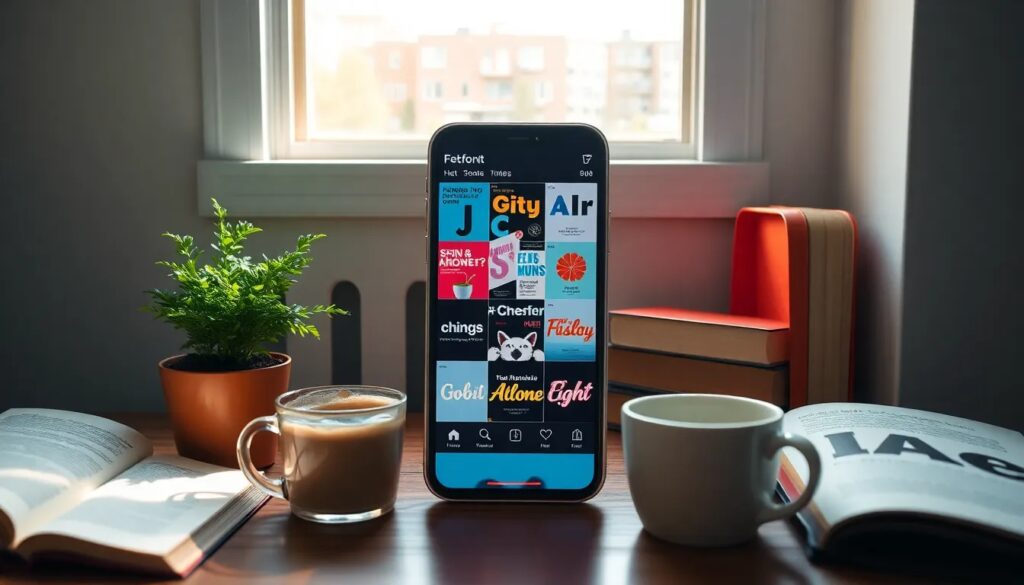
Cool fonts instagram para destacar tu perfil
Generador de fuentes para Instagram: cool fonts instagram
Las cool fonts instagram se han vuelto una herramienta imprescindible para quienes desean personalizar su perfil y hacerlo más atractivo. Con un generador de fuentes, puedes experimentar con diferentes estilos de texto que capturan la atención de tus seguidores.
Utilizando caracteres Unicode, estos generadores ofrecen una amplia variedad de fuentes que puedes usar en tu biografía, publicaciones y más. Esto te permite no solo diferenciarte, sino también mostrar un estilo único que refleje tu personalidad.
¿Para qué sirven las fuentes para Instagram?
Las fuentes para Instagram sirven principalmente para destacar tu perfil y hacer que tu contenido sea más atractivo. Al personalizar tu texto, puedes atraer más seguidores y mantener el interés de tus visitantes. Las fuentes estilizadas añaden un toque de originalidad que puede ser muy efectivo.
Además, usar fuentes diferentes puede ayudar a que tu biografía sea más memorable y fácil de leer. La claridad y el estilo son aspectos que la audiencia valora, y las fuentes adecuadas pueden jugar un papel crucial en esto.
• Ayudan a diferenciarte de otros perfiles.
• Permiten expresar tu personalidad de forma visual.
• Facilitan la creación de contenido que resuena con tu audiencia.
¿Cómo generar cool fonts instagram para mi perfil?
Generar cool fonts instagram es un proceso sencillo que puedes realizar en minutos. Existen múltiples generadores gratuitos en línea que te permiten introducir tu texto y recibir distintas opciones de fuentes estilizadas.
Recuerda que algunos estilos pueden no ser visibles en todos los dispositivos. Es recomendable probar cómo se ven en diferentes plataformas antes de hacer cambios permanentes en tu perfil.
¿Cuáles son las mejores fuentes estilizadas para Instagram?
En el ámbito de las fuentes modernas para Instagram que llamen la atención, hay varias opciones populares que destacan. Algunas de las más utilizadas incluyen:
• Fuentes cursivas, que aportan un toque elegante.
• Fuentes góticas, ideales para un estilo más atrevido.
• Fuentes decorativas, perfectas para hacer tu biografía única.
• Fuentes de tipo máquina de escribir, que evocan un estilo retro.
Además, puedes encontrar fuentes que imitan el estilo de la escritura a mano, lo que puede hacer que tu perfil se sienta más personal. La elección de la fuente debe alinearse con la estética general que deseas proyectar.
¿Qué tipos de fuentes se pueden crear con un generador?
Un generador de fuentes gratis para Instagram que puedes usar ahora te permite crear diversos estilos que se adaptan a tus necesidades. Algunos de los tipos de fuentes que puedes generar incluyen:
• Fuentes normales: ideales para un uso cotidiano
• Fuentes en negrita: para destacar información importante
• Fuentes con símbolos decorativos: que añaden un elemento visual único
Las combinaciones son prácticamente infinitas, lo que te permite ser creativo y experimentar hasta encontrar el estilo que más te guste. Recuerda que las fuentes pueden influir en la percepción de tu perfil, así que elige sabiamente.
¿Es fácil usar un generador de fuentes para Instagram?
Definitivamente, usar un generador de fuentes para Instagram es muy fácil. La interfaz suele ser intuitiva, permitiendo que cualquier persona, independientemente de su nivel de habilidad digital, pueda personalizar su texto.
La mayoría de los generadores son gratuitos y requieren solo unos pocos clics. Solo tienes que ingresar el texto que deseas modificar, y en segundos recibirás diferentes estilos para elegir. Esto hace que la personalización sea una tarea rápida y sin complicaciones.
Además, puedes experimentar con diferentes combinaciones hasta encontrar la que mejor te represente. La facilidad de uso es uno de los principales atractivos de estas herramientas.
¿Qué son los símbolos Unicode y cómo se usan en las fuentes?
Los símbolos Unicode son caracteres que permiten la representación de texto en diferentes idiomas y estilos. Se utilizan en las cool fonts instagram para crear caracteres estilizados y únicos que no se encuentran en fuentes estándar.
La ventaja de usar Unicode es que garantiza una mayor compatibilidad entre plataformas. Esto significa que, al copiar y pegar texto generado, es probable que se mantenga la apariencia en la mayoría de los dispositivos.
En conclusión, utilizar cool fonts instagram es una excelente manera de personalizar tu perfil y atraer más seguidores. Experimenta con diferentes estilos, encuentra lo que te representa y no dudes en jugar con los generadores disponibles para hacer que tu perfil sea verdaderamente único.